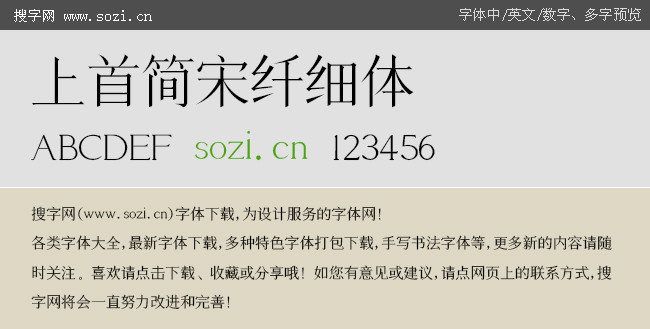
上首簡宋纖細(xì)體
搜字網(wǎng)給大家提供一款上首簡宋纖細(xì)體中文字體下載,上首簡宋纖細(xì)體字體風(fēng)格緊湊嚴(yán)謹(jǐn),筆畫舒展,橫畫的尖突與勾、點、提的圓潤處理相呼應(yīng),剛?cè)岵、工整而不失精巧,最大程度的展現(xiàn)筆畫的柔和秀美,有極強的視覺表現(xiàn)力,可應(yīng)用于各類報紙、雜志、廣告等正文設(shè)計。